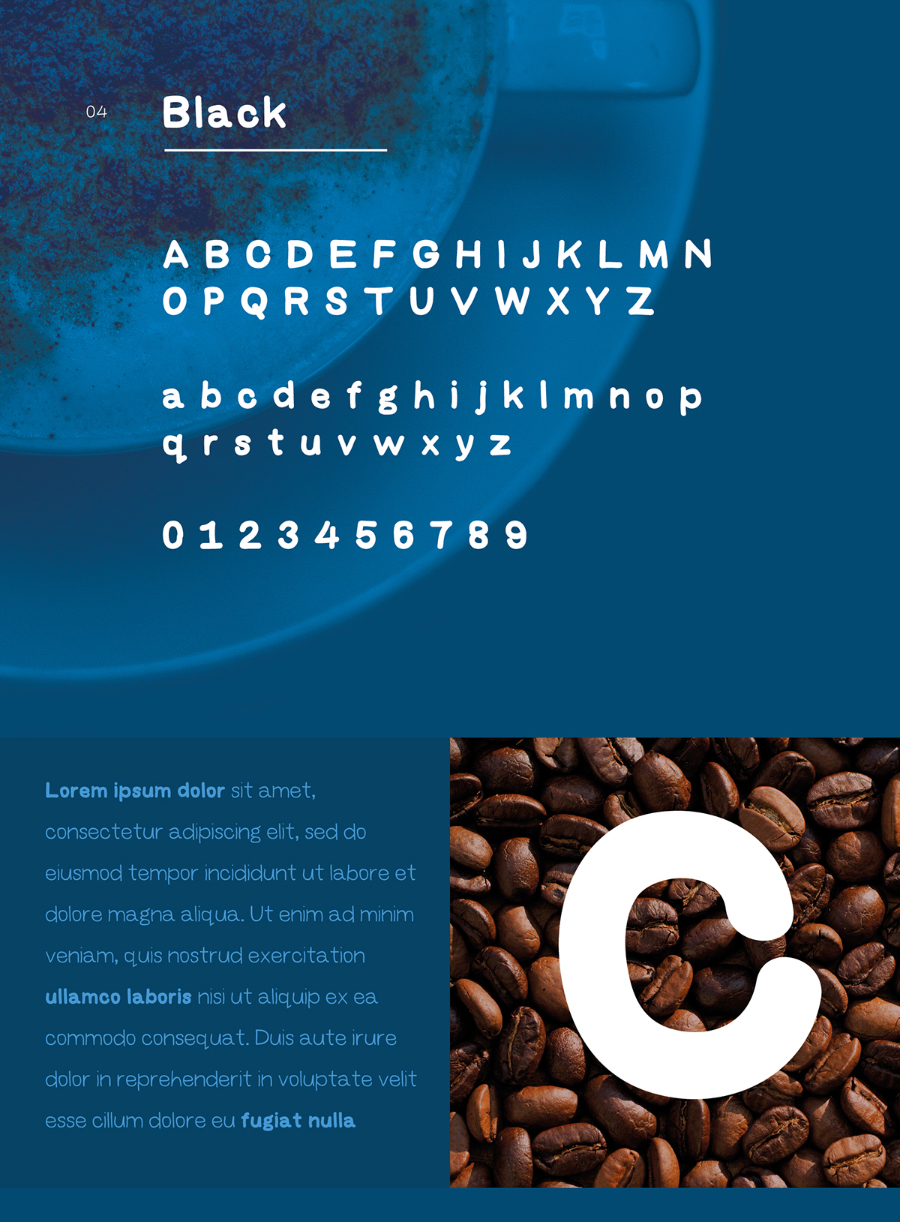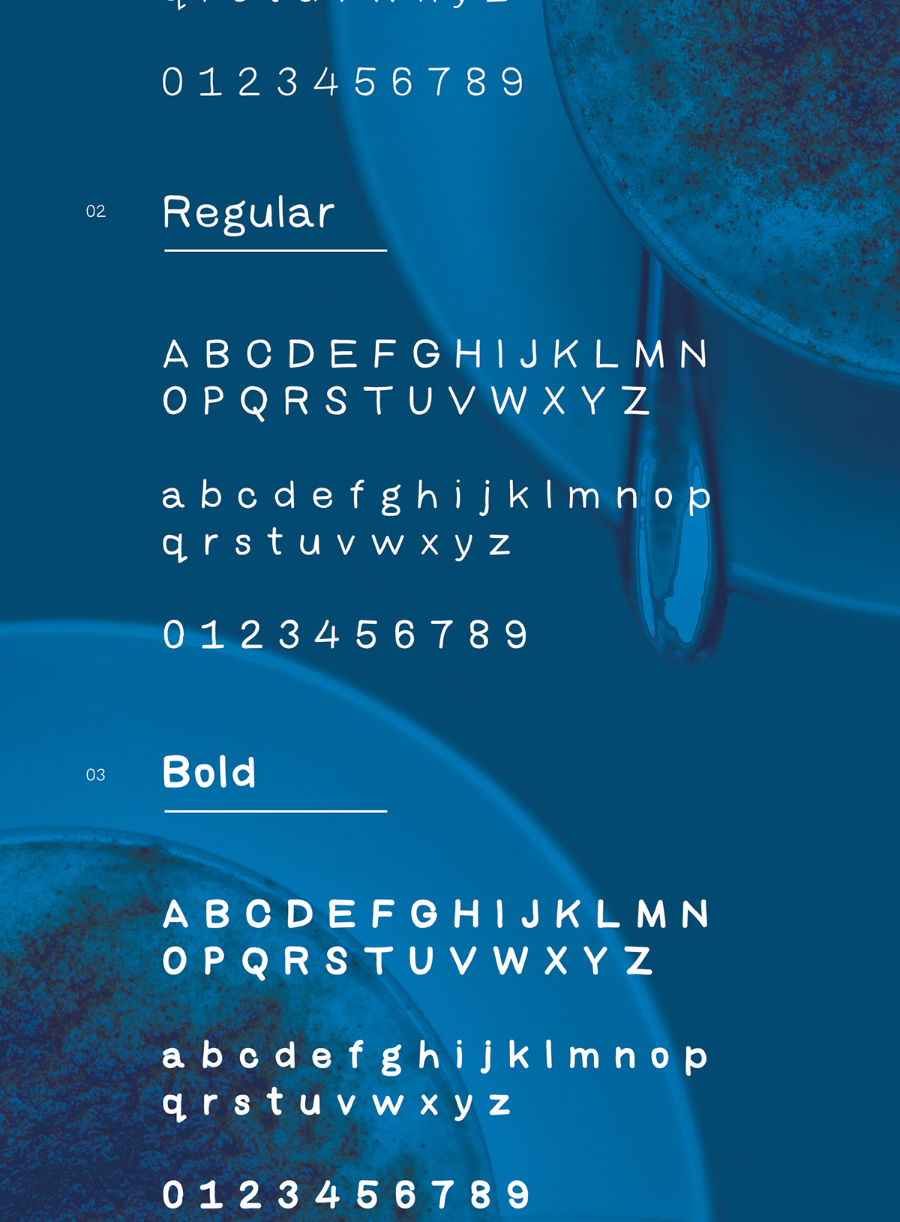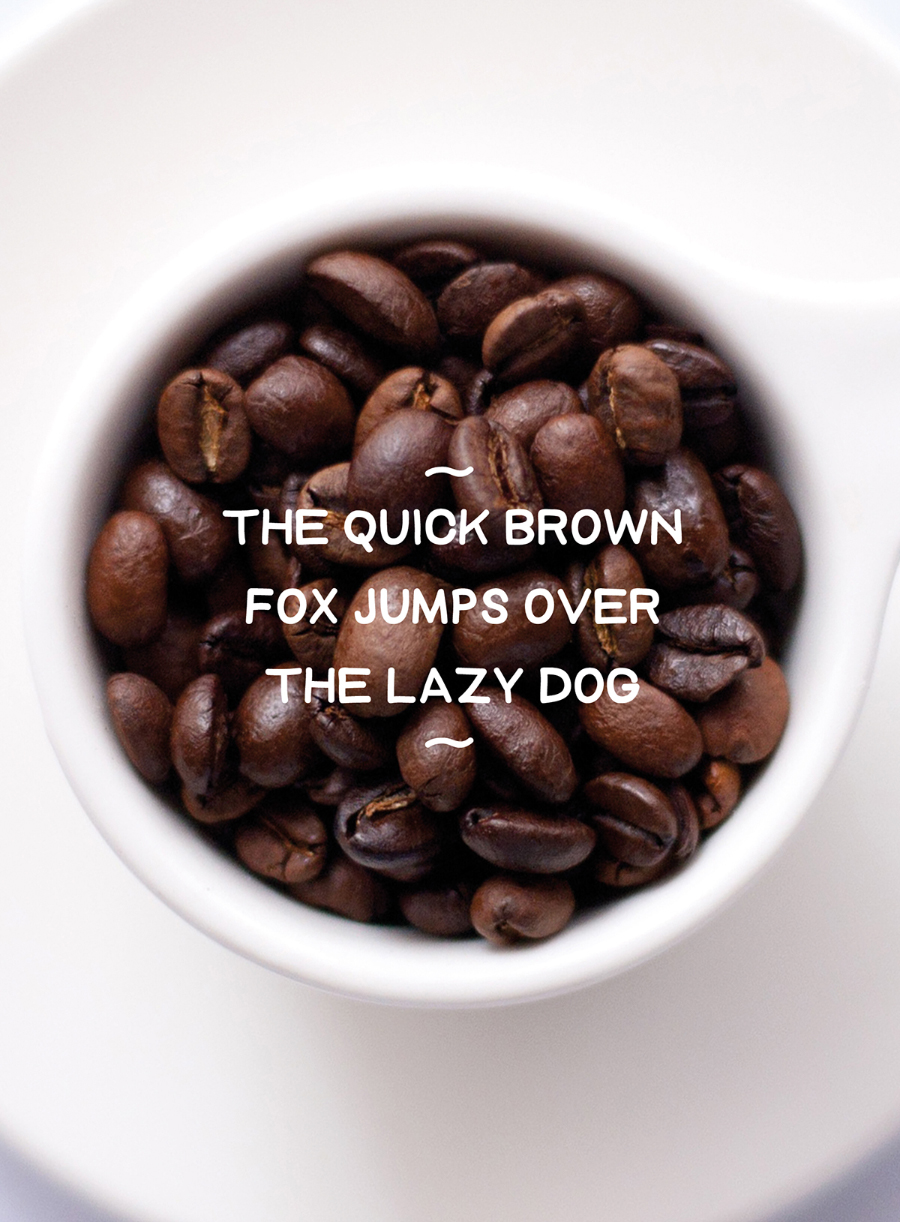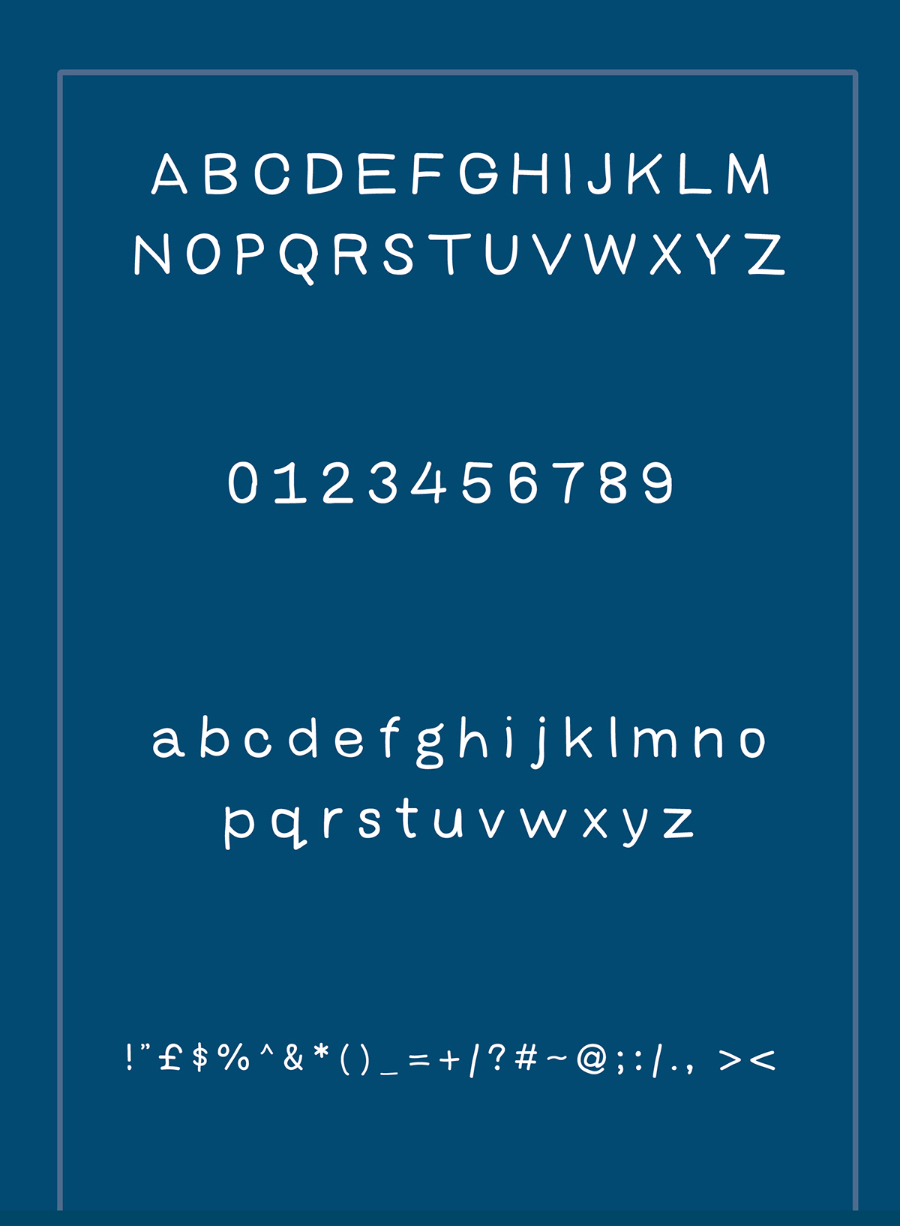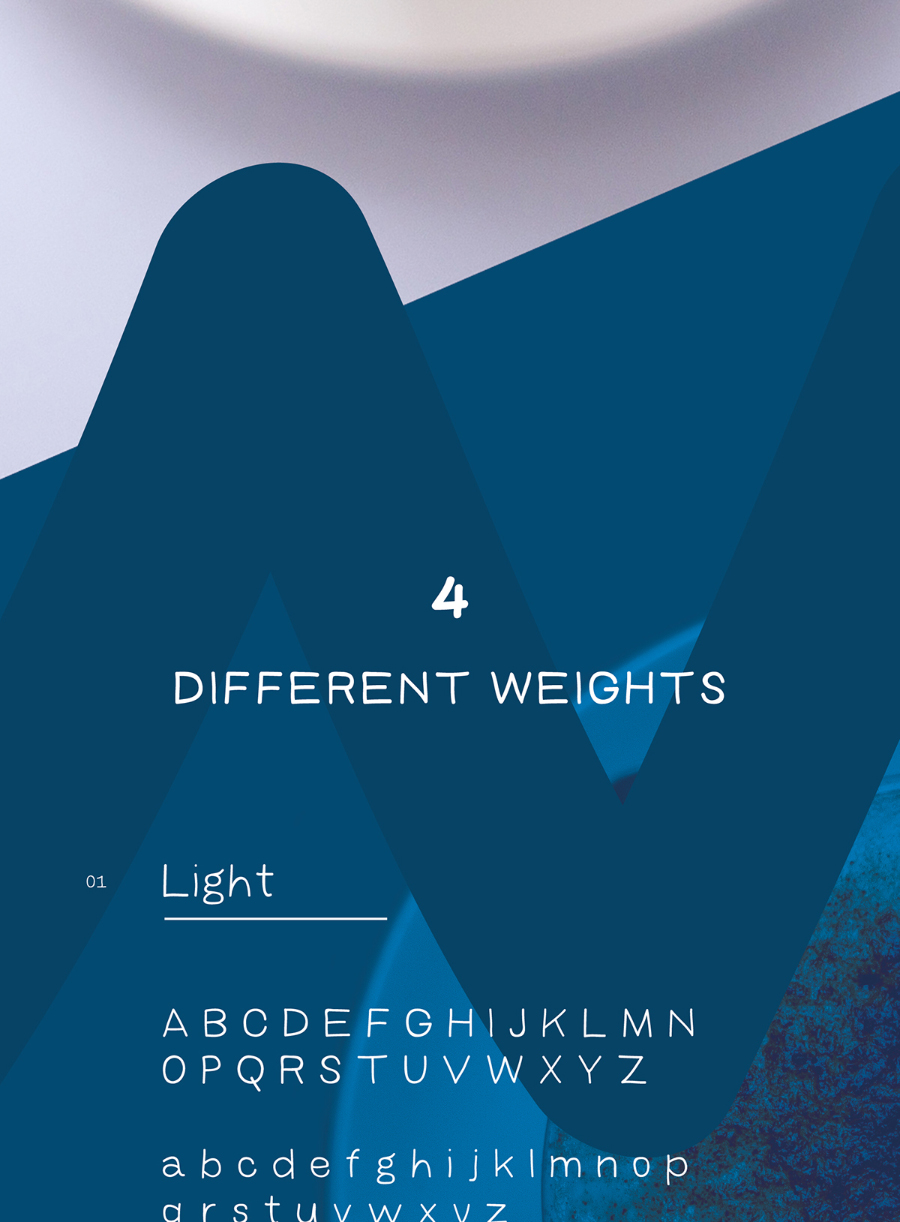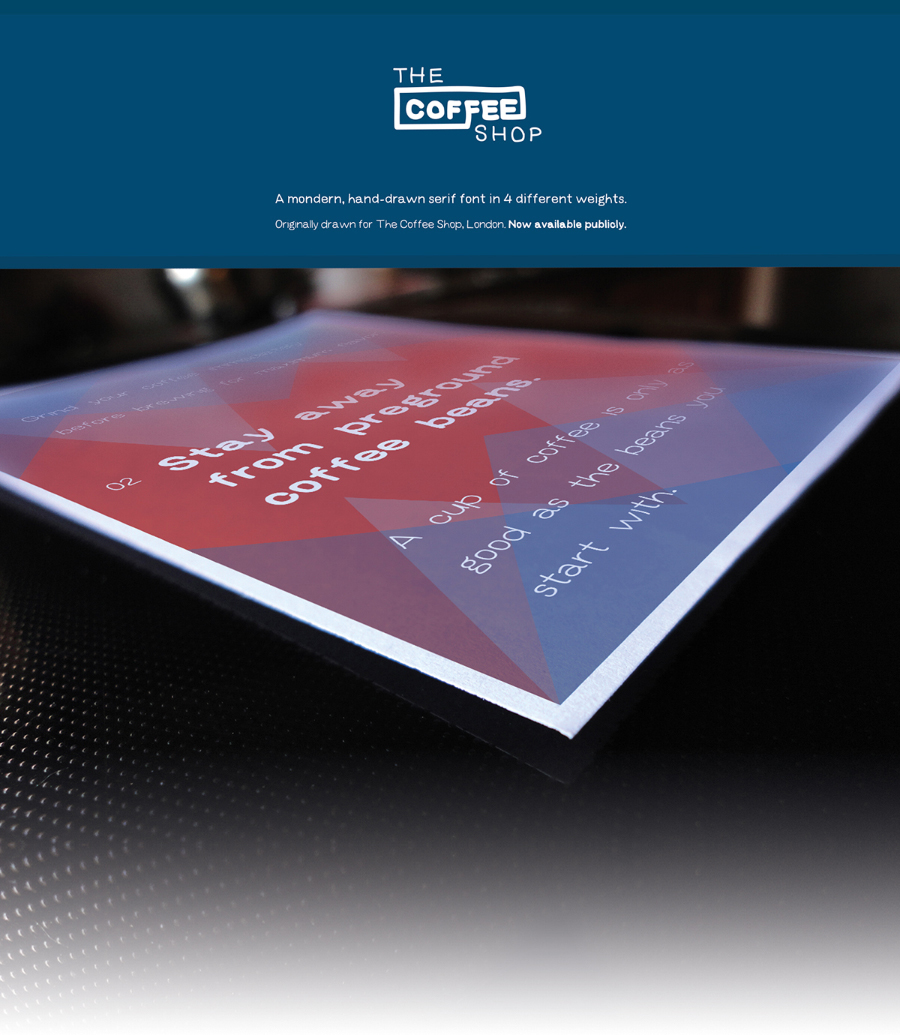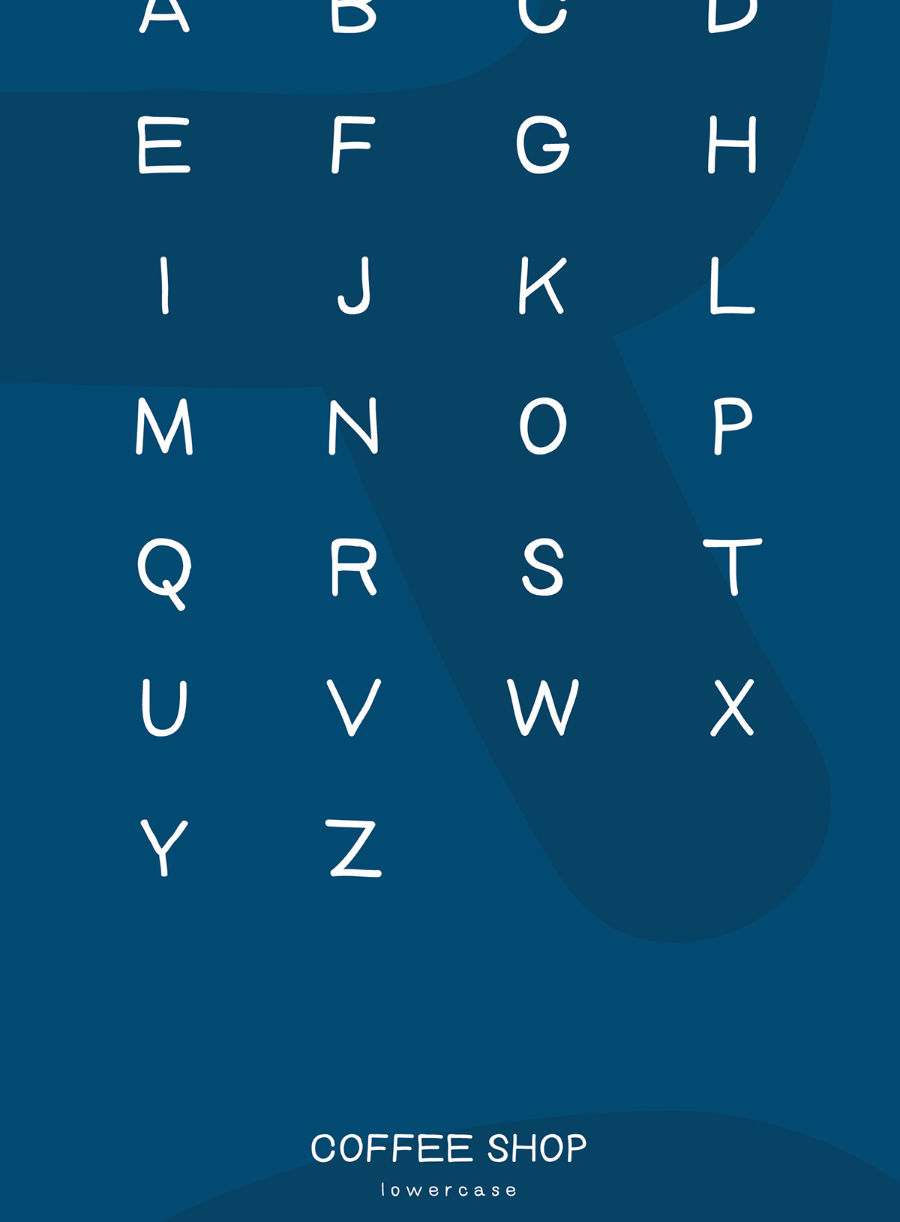
咖啡店免费字体家庭
Coffee Shop Free Font Family
咖啡店免费字体家族是一组最初为伦敦咖啡店绘制的字体。现在每个人都可以使用该字体。咖啡店将是伟大的咖啡馆品牌,但你也可以用它来做其他事情。海报,标题,标识,社交媒体横幅也将与咖啡店看起来很棒。这些字体是免费的个人和商业用途。